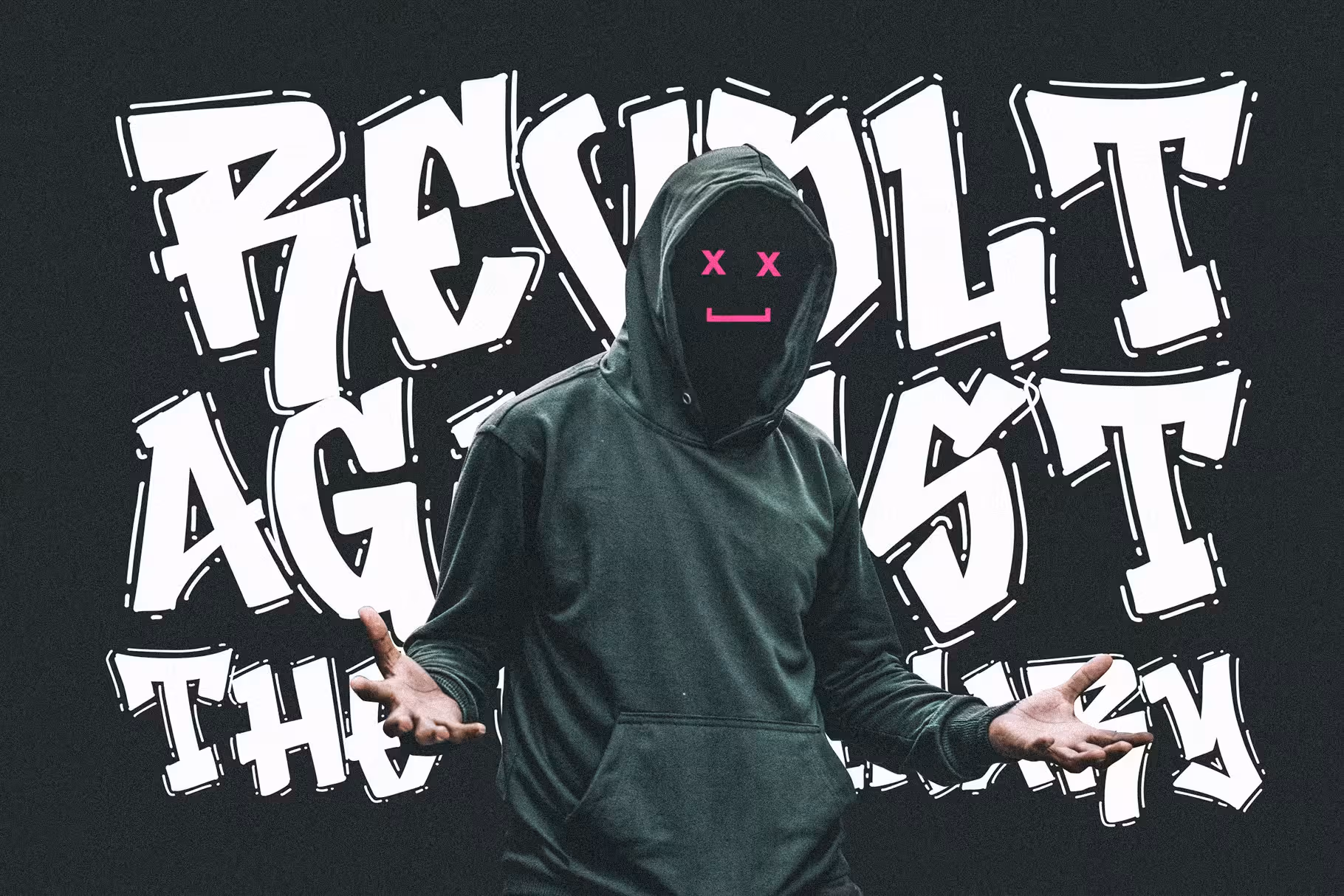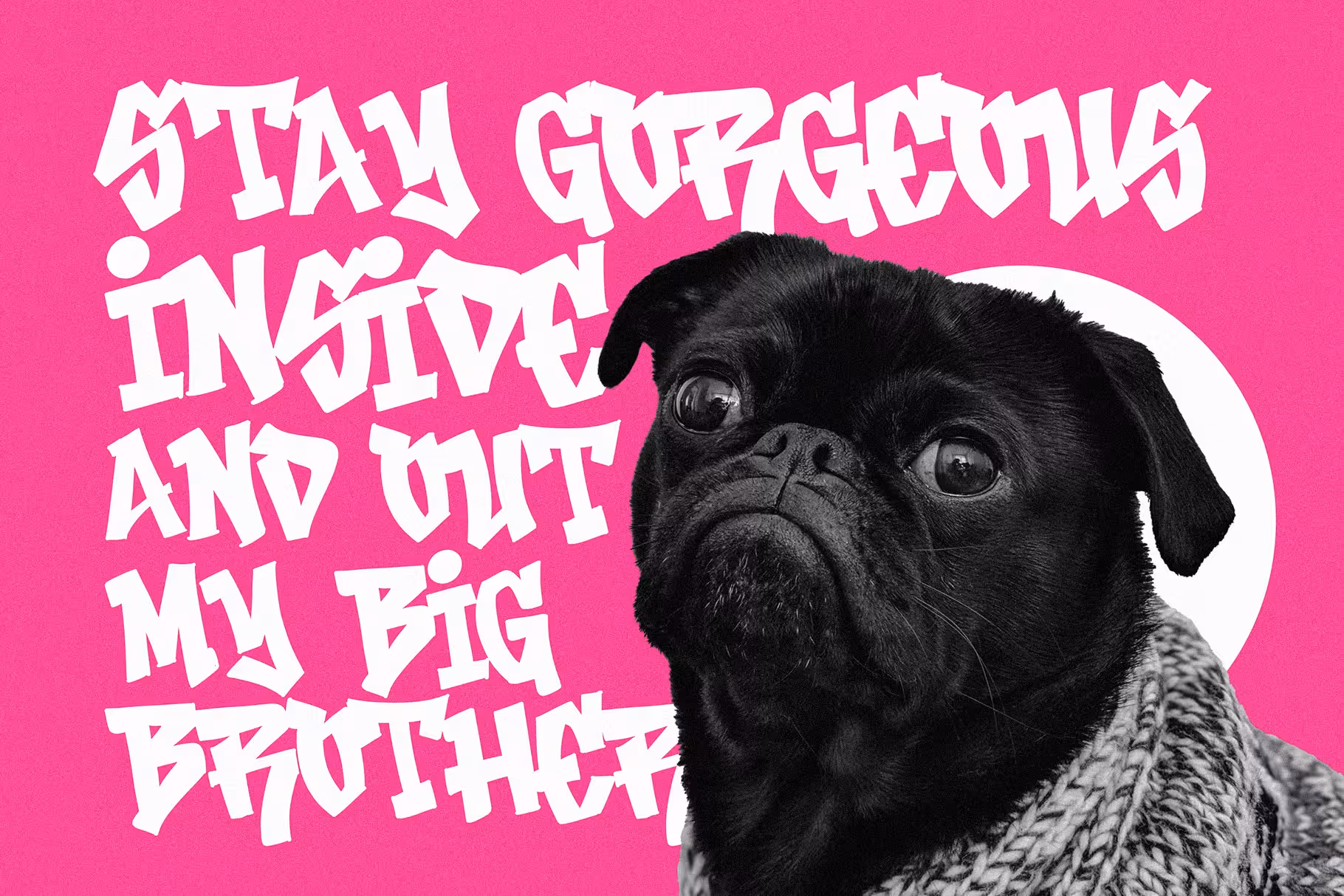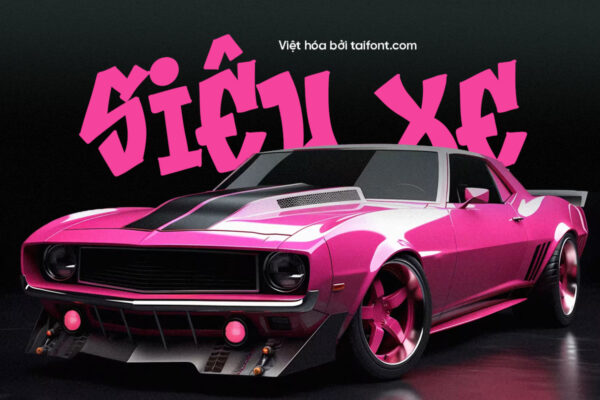
Giới thiệu về Font TF Reign Beats Việt hóa
TF Reign Beats Việt hóa là một font chữ trang trí nổi bật với thiết kế phóng khoáng, tự do và đầy ngẫu hứng, gợi cảm giác về những nét chữ được vẽ bằng cọ, phun sơn, hoặc viết tay một cách phá cách. Font này toát lên phong thái năng động, bụi bặm và một chút hoài niệm của nghệ thuật đường phố, lý tưởng để tạo điểm nhấn độc đáo và thu hút mọi ánh nhìn trong các thiết kế đòi hỏi sự cá tính và sự sáng tạo.
Với đặc điểm là nét viết tay tự nhiên, phong thái dễ chịu và tính ứng dụng cao, Reign Beats là lựa chọn hoàn hảo cho các thiết kế muốn truyền tải sự độc đáo, cá tính và sự gần gũi:
- Thiết kế nghệ thuật đường phố: Hoàn hảo để tạo các biển hiệu vẽ tay, bảng phấn, hoặc các tác phẩm trang trí mang phong cách graffiti, street art. Font này giúp tạo không khí sôi động, phá cách và đầy năng lượng.
- Thiết kế thời trang đường phố (streetwear): Lý tưởng cho thương hiệu thời trang, phụ kiện, hoặc các ấn phẩm truyền thông liên quan đến văn hóa đường phố, giải trí. Font này giúp tạo dấu ấn cá nhân, sự phá cách và độc đáo cho thương hiệu.
- Thiết kế poster và banner: Tuyệt vời để tạo các tiêu đề chính (headline), slogan, hoặc thông điệp quảng cáo trên poster, banner, hoặc bất kỳ ấn phẩm nào cần sự chú ý tối đa. Nét chữ tự nhiên của font giúp thông điệp của bạn nổi bật, dễ đọc và truyền tải một cách hiệu quả.
- Thiết kế bao bì sản phẩm: Phù hợp để sử dụng trên nhãn mác, bao bì của các sản phẩm có phong cách vui tươi, năng động, đặc biệt là các sản phẩm liên quan đến giới trẻ. Font này giúp sản phẩm trở nên nổi bật và thu hút.
Với TF Reign Beats Việt hóa, bạn có thể dễ dàng thổi hồn mộc mạc, sự độc đáo và vẻ đẹp tự nhiên vào các thiết kế, tạo ra những sản phẩm không chỉ đẹp mắt mà còn đầy cảm xúc và sức hút đặc biệt.
Font Việt hóa TF Reign Beats